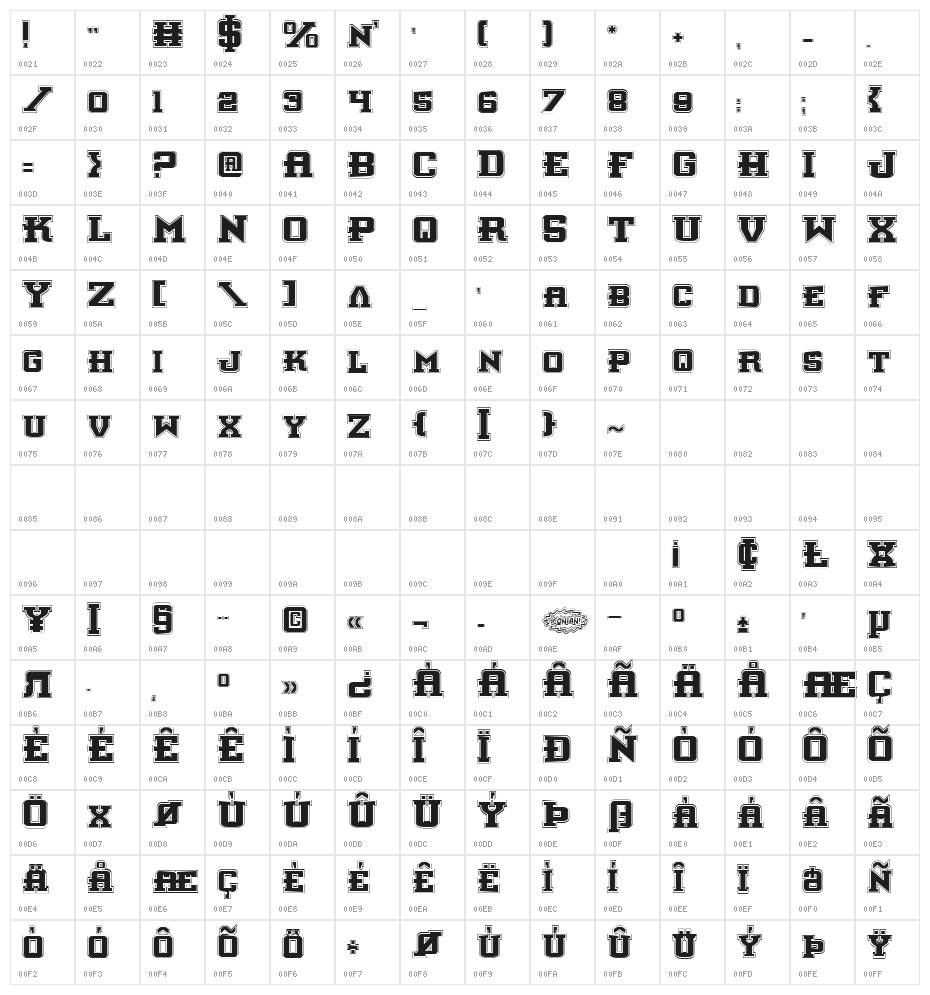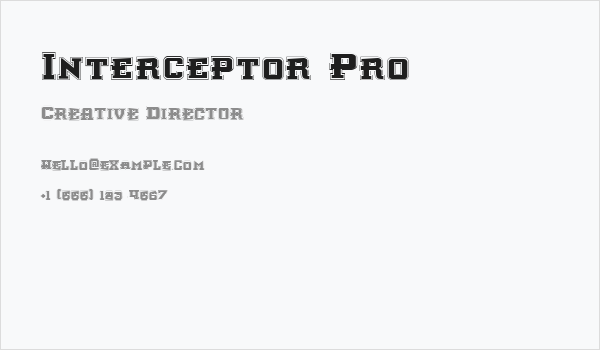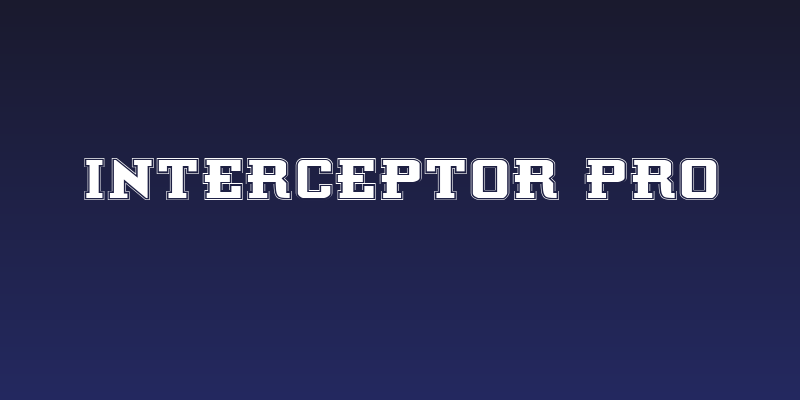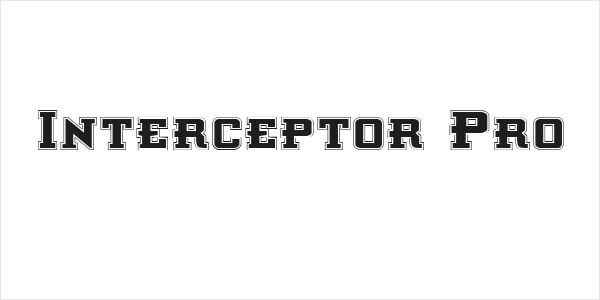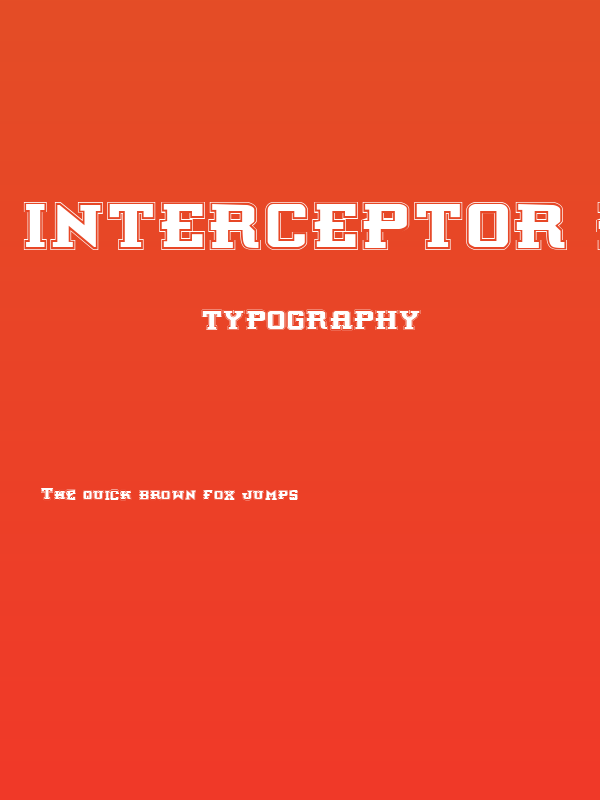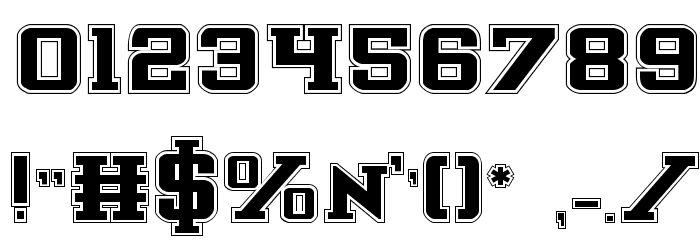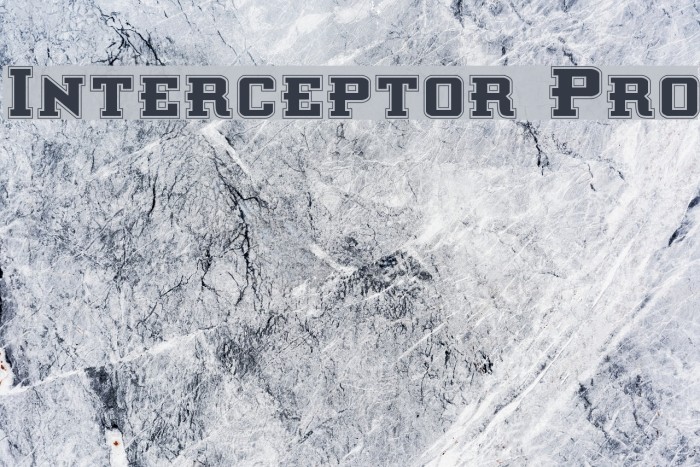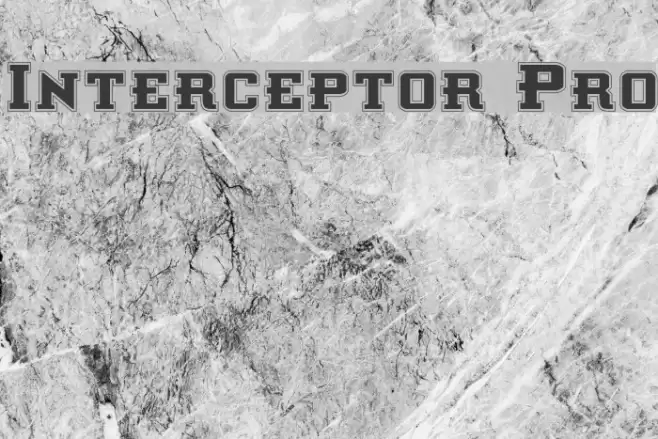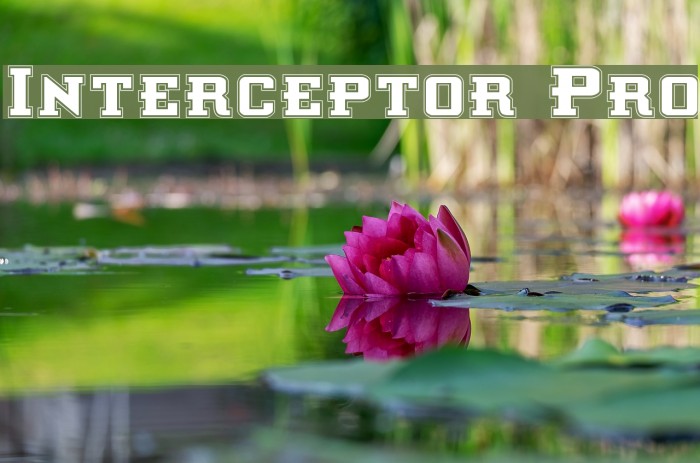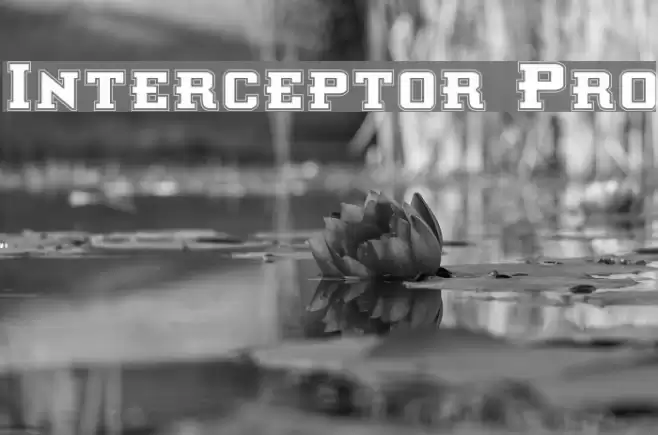
Interceptor Pro Font
| Proyectos propuestos | Perfect for sports team branding, event posters, merchandise design, and any project needing a bold statement. |